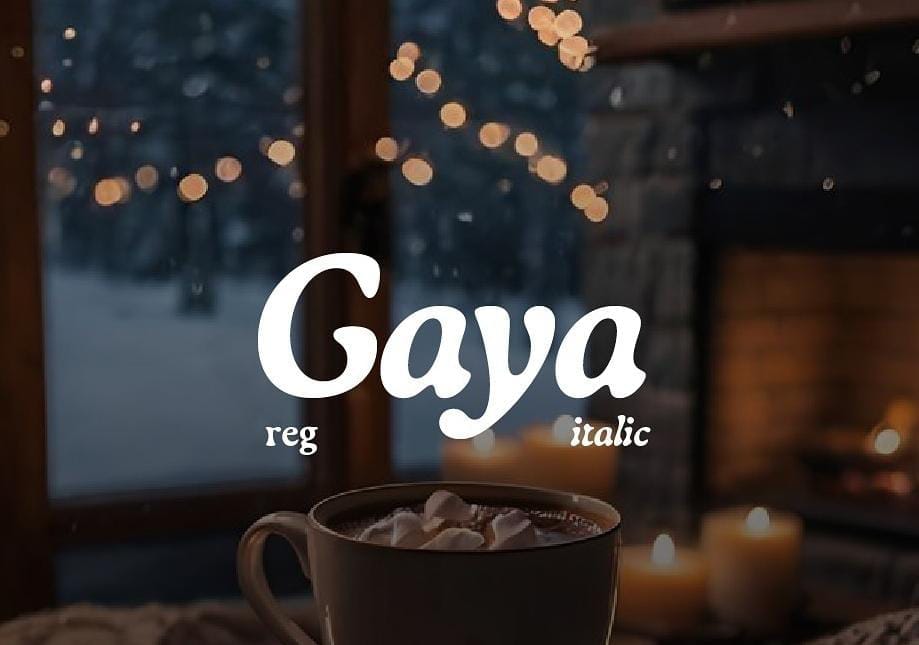
Gaya tipografi yang mewakili setiap musim akan berbeda, untuk musim dingin gaya huruf akan tampil dingin, elegan dan seringkali tajam. Font tebal memiliki banyak variasi untuk digunakan pada desain musim dingin biasanya menggunakan gaya huruf tajam, bulat hingga elegan. Pastikan memilih gaya huruf yang merepresentasikan nuansa dan mood desain musim dengan baik.
Tipografi musim dingin akan tampil beda dengan musim panas yang biasanya tampil segar dan menyenangkan. Seringkali gaya tipografi musim dingin memiliki kesan lebih elegan, mewah dan tajam. Gaya tipografi juga bisa memiliki style font berkesan cozy dan mengalir sehingga lebih santai.
CIRI TIPOGRAFI MUSIM DINGIN
Desain tema musim dingin untuk kebutuhan poster, banner, konten hingga desain logo akan memiliki gaya tipografi yang mirip. Tema musim dingin biasanya akan cocok menggunakan gaya tipografi tajam, elegan, tebal dan bersih. Pilih style tipografi yang sesuai dengan kebutuhan brand dan tema desain agar harmonis.
Bersih dan Tajam
Kebanyakan style tipografi untuk desain musim dingin akan memiliki gaya huruf bersih dan tajam terutama yang bergaya modern. Font bersih akan mudah dibaca, biasanya desain musim dingin akan memiliki style bersih dan minimalis.
Gaya font sederhana akan mudah untuk konsisten dan serbaguna digunakan dalam berbagai kebutuhan. Tipografi minimalis akan menciptakan desain musim dingin yang profesional dan handal.
Elegan dan Halus
Gaya font untuk musim dingin juga ada yang memiliki style elegan agar menciptakan kesan elegan dan mewah. Pada brand premium, gunakan font musim dingin yang elegan, contohnya seorang serif modern yang elegan.
Font elegan akan menciptakan nuansa yang dingin, kaku dan fresh, biasanya digunakan pada desain christmas. Konten dan poster bertema christmas akan cocok menggunakan font elegan dan tipis. Gaya font script tipis dan serif elegan akan cocok menciptakan desain musim dingin yang elegan.
Tebal dan Menyenangkan
Meski desain musim dingin didominasi tipografi yang tajam, halus dan elegan, tetapi gaya font tebal dan melengkung bisa digunakan. Font tebal dan sudut melengkung akan menciptakan kesan menyenangkan dan ramah.
Biasanya gaya tipografi tersebut cocok digunakan untuk desain musim dingin untuk brand food and beverage. Font ini akan memiliki huruf sederhana dan tampil bersih sehingga akan mudah dibaca. Gaya huruf tebal dan bulat akan merepresentasikan brand musim dingin yang cozy dan ramah.
Chic dan Modern
Tipografi musim dingin juga bisa menggunakan gaya huruf modern yang unik dan tampil chic. Gunakan style font chic untuk menciptakan logo sederhana tetapi tampil beda dan unik. Utamanya pada logo wordmark yang hanya menggunakan tipografi.
Style font chic, biasanya memiliki bentuk huruf unik dan tidak seperti huruf biasanya sehingga tampil lebih menarik. Kontras ketebalan garis, jarak antar huruf dan bentuk huruf yang chic akan menciptakan desain musim dingin yang unik.
Cozy dan Elegan
Sementara itu gaya font yang elegan akan menciptakan nuansa musim dingin yang cozy. Gaya font elegan dan cozy cocok untuk desain poster, kartu ucapan hingga kemasan brand premium. Font elegan akan memiliki gaya huruf yang tampak halus dan mengalir seperti font tulisan tangan.
Gunakan font elegan dan bergaya cozy yang lembut untuk brand makanan atau minuman. Pada desain musim dingin, desain konten brand makanan dan minuman bisa menggunakan font elegan agar tampil handal.
REKOMENDASI FONT MUSIM DINGIN
Untuk tema desain musim dingin, gunakan font yang menciptakan nuansa dingin seperti huruf tajam, garis halus dan elegan. Tema musim dingin akan lebih cocok dengan font bernuansa dingin daripada bulat dan tebal. Font yang cocok dengan style musim dingin seringkali bergaya modern dan memiliki kontras ketebalan gaya hurufnya.
Crake
Gaya tipografi musim dingin ini tampil elegan dan unik, cocok untuk desain poster food and beverage pada musim dingin. Garis hurufnya memiliki style yang halus dan kontras ketebalan sehingga tampil unik. Font juga memiliki ujung lancip sehingga menciptakan desain elegan dan berkesan dingin.
Tampilan tipografi ini menciptakan tampilan huruf yang tebal, halus dan tajam untuk meningkatkan daya tarik pada brand. Style font yang unik ini akan membuat tipografi brand tampil beda. Gunakan font tajam dan tebal ini untuk desain brand ice cream, bakery hingga beverage.
Miju
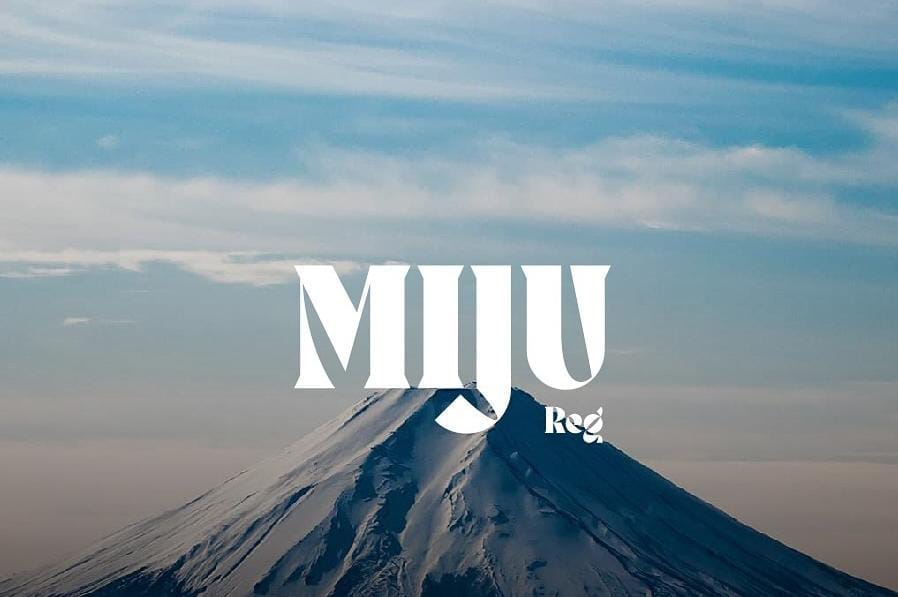
Desain bertema musim dingin juga bisa menggunakan font tebal tetapi yang tampil tajam bukan bulat. Gaya hurufnya memiliki kontras ketebalan dan memiliki sudut yang tajam sehingga tampil elegan. Jarak yang rapat pada hurufnya menciptakan kesan font musim dingin yang modern.
Font tersebut akan menciptakan desain brand yang unik, tebal dan menciptakan kesan menyenangkan. Untuk desain musim dingin tipografi ini akan menciptakan dampak yang serius. Akan sempurna digunakan untuk menciptakan brand yang chill, menonjol dan berkesan profesional. Cocok untuk brand minuman premium seperti wine dan beer untuk musim dingin.
Tipografi untuk tema musim dingin didominasi tipografi yang tajam, halus, bersih dan bergaya modern. Meskipun begitu ada juga penggunaan font bulat yang memiliki sudut melengkung akan menciptakan kesan ramah dan cozy. Pastikan untuk kebutuhan desain berbeda akan memilih font yang tepat sehingga tampil profesional dan relevan.